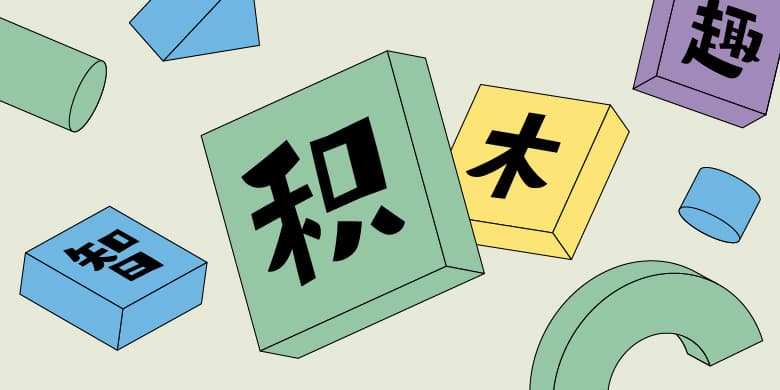
2020年方正推出与日本合作的一款字体。这款字体在版画风格中加进了几何形的圆角,无论是单字还是排成的词句都能透露出一种幼稚、笨拙的感觉。可以在排版时给读者以「幼稚」「天真」「乏力」的感觉,还能表现出节奏感和喜剧效果。
版画調な中に幾何学的な丸みを加え、文字単体および文字組みをした場合にも幼く抜けた空気感をもつ書体です。文字を並べた際に、《幼さ》《無邪気》《脱力感》をイメージさせ、さらにリズミカルでコミカルな感じを表現することができます。